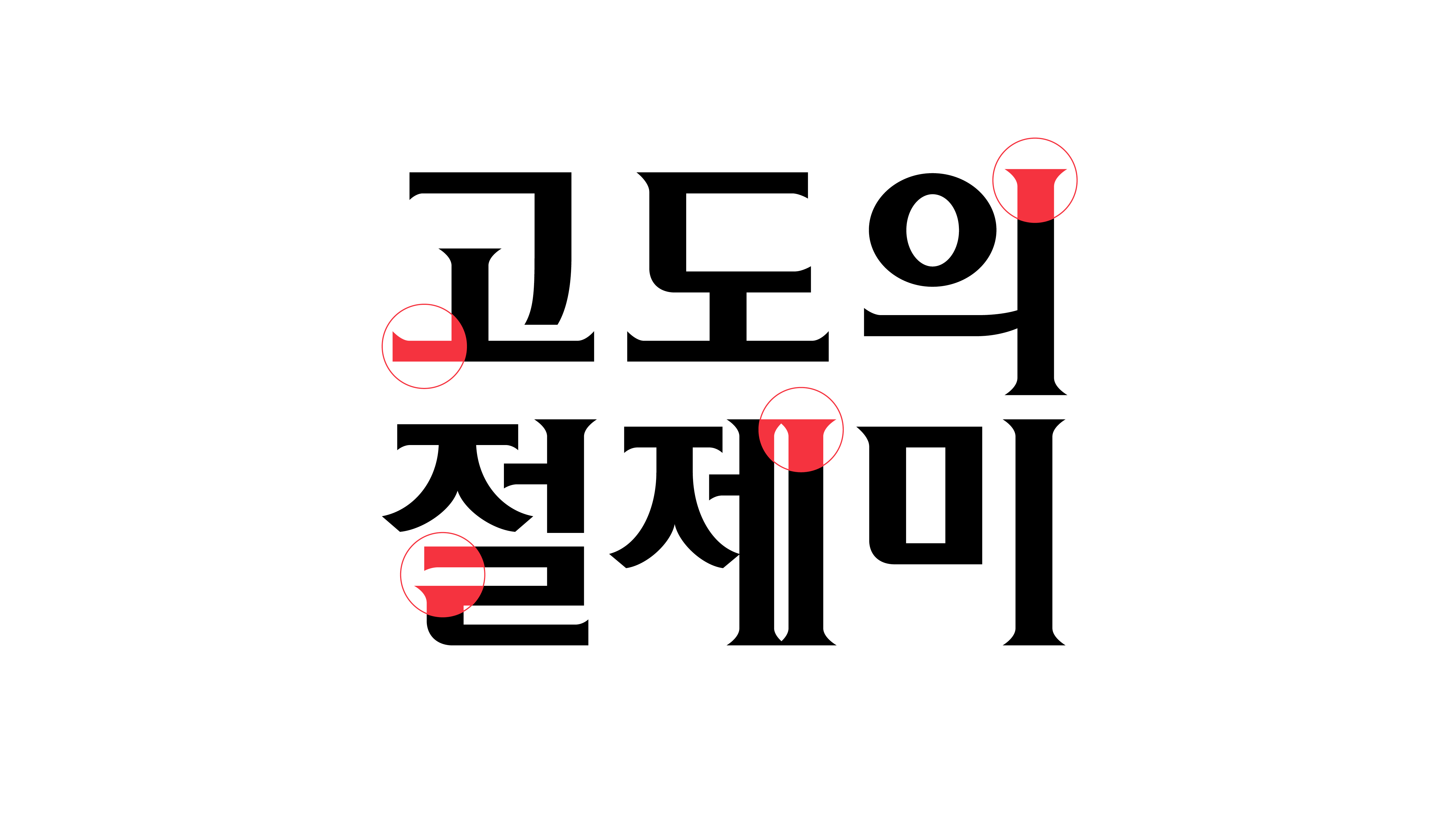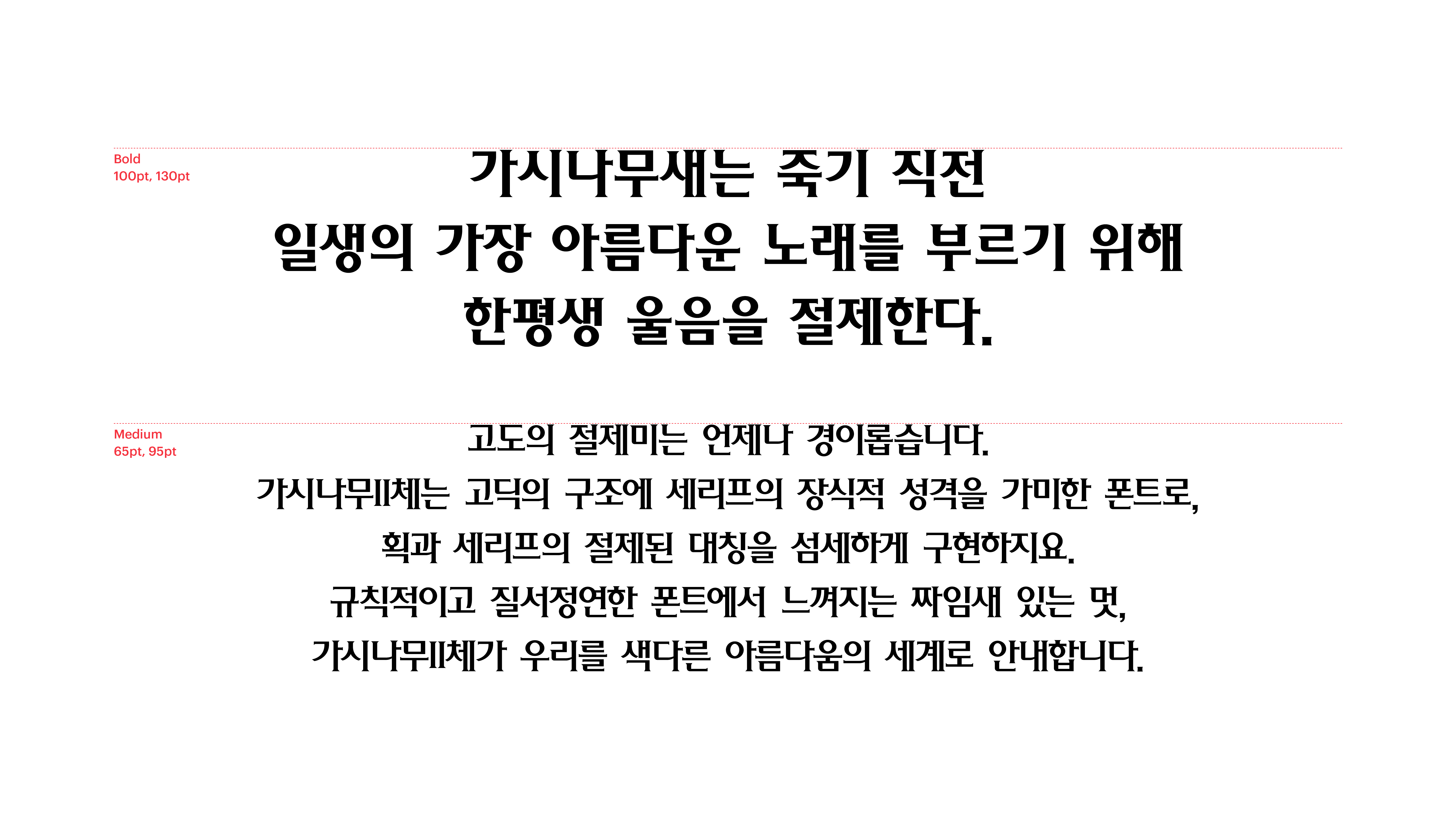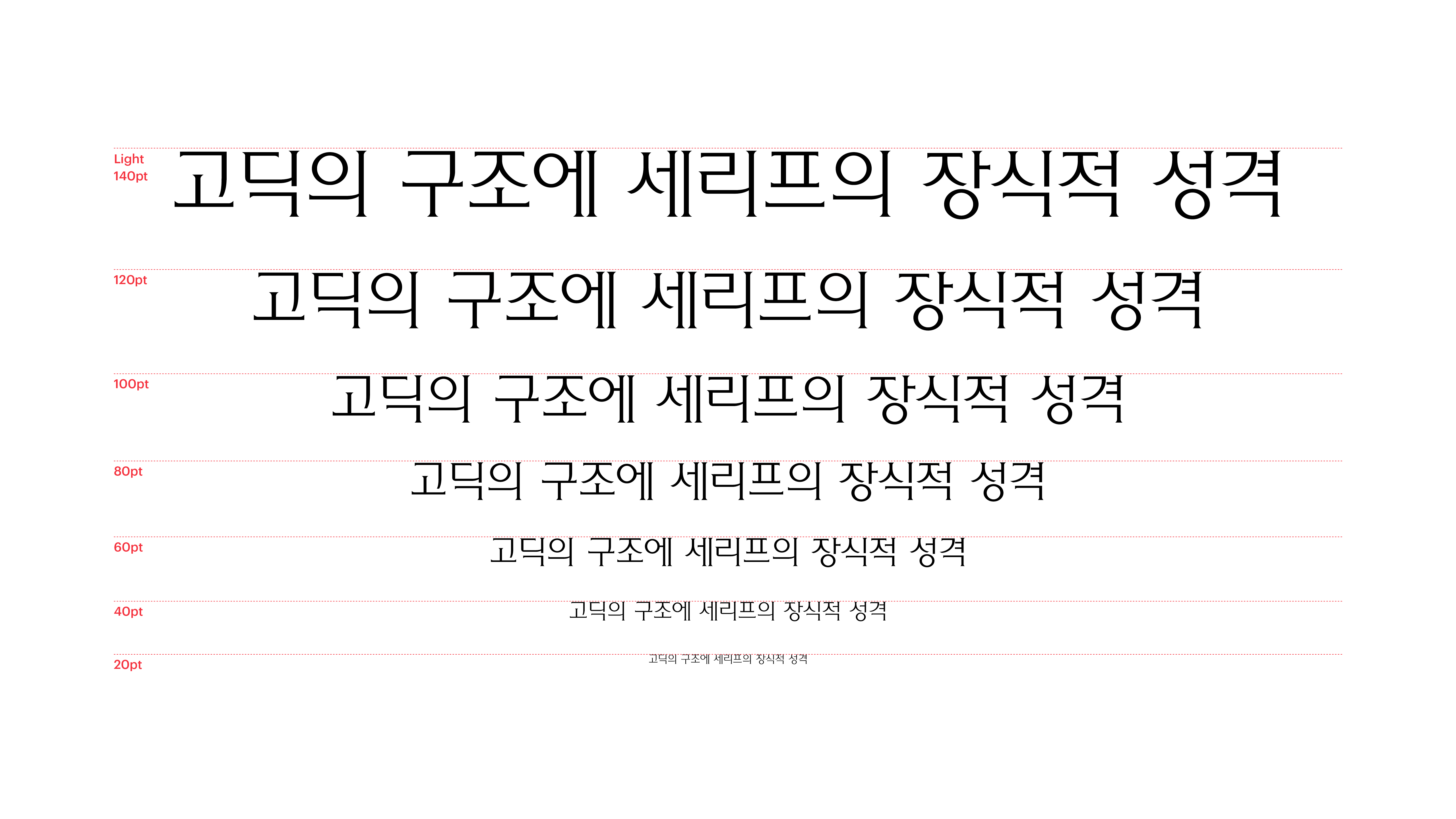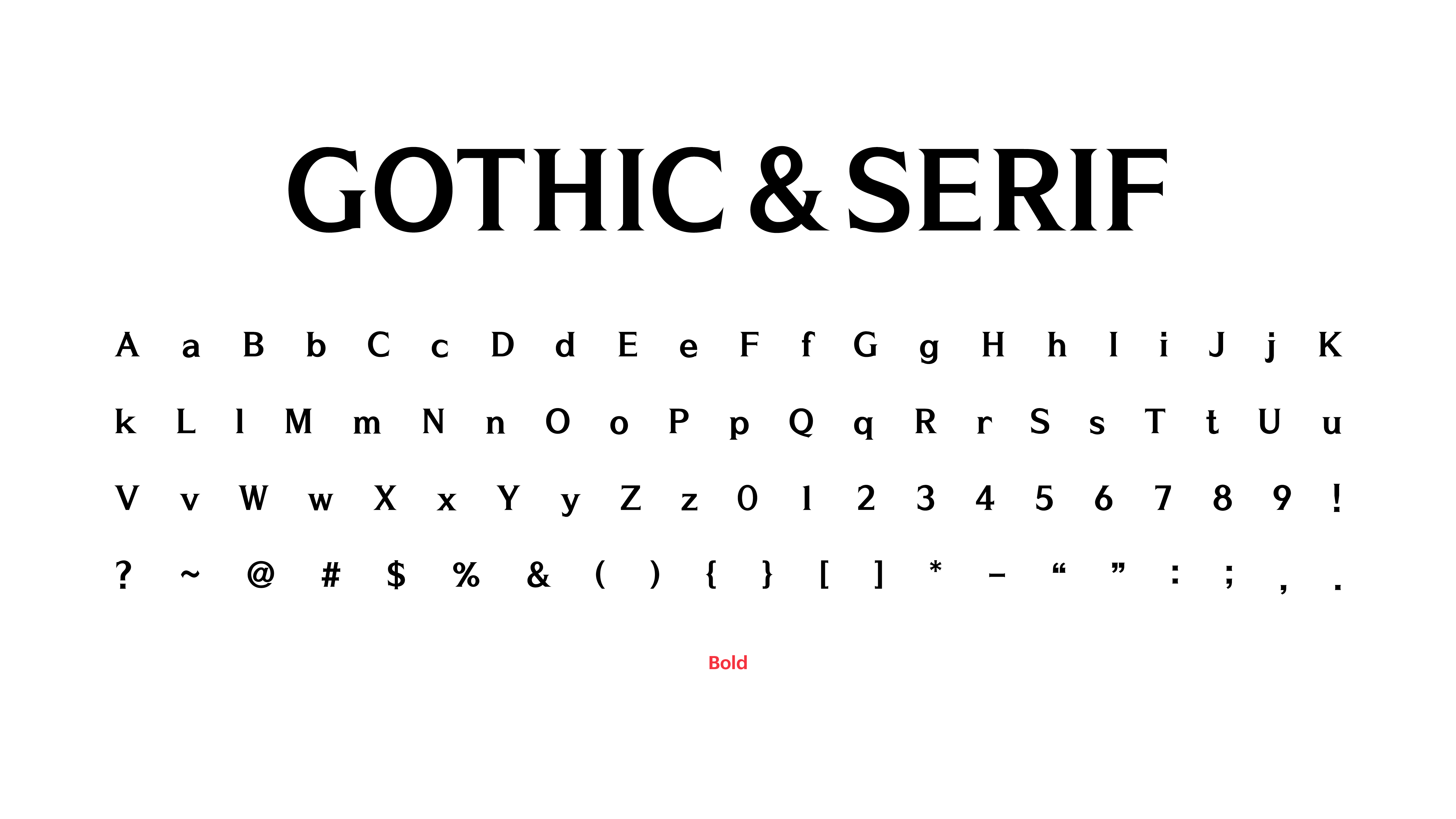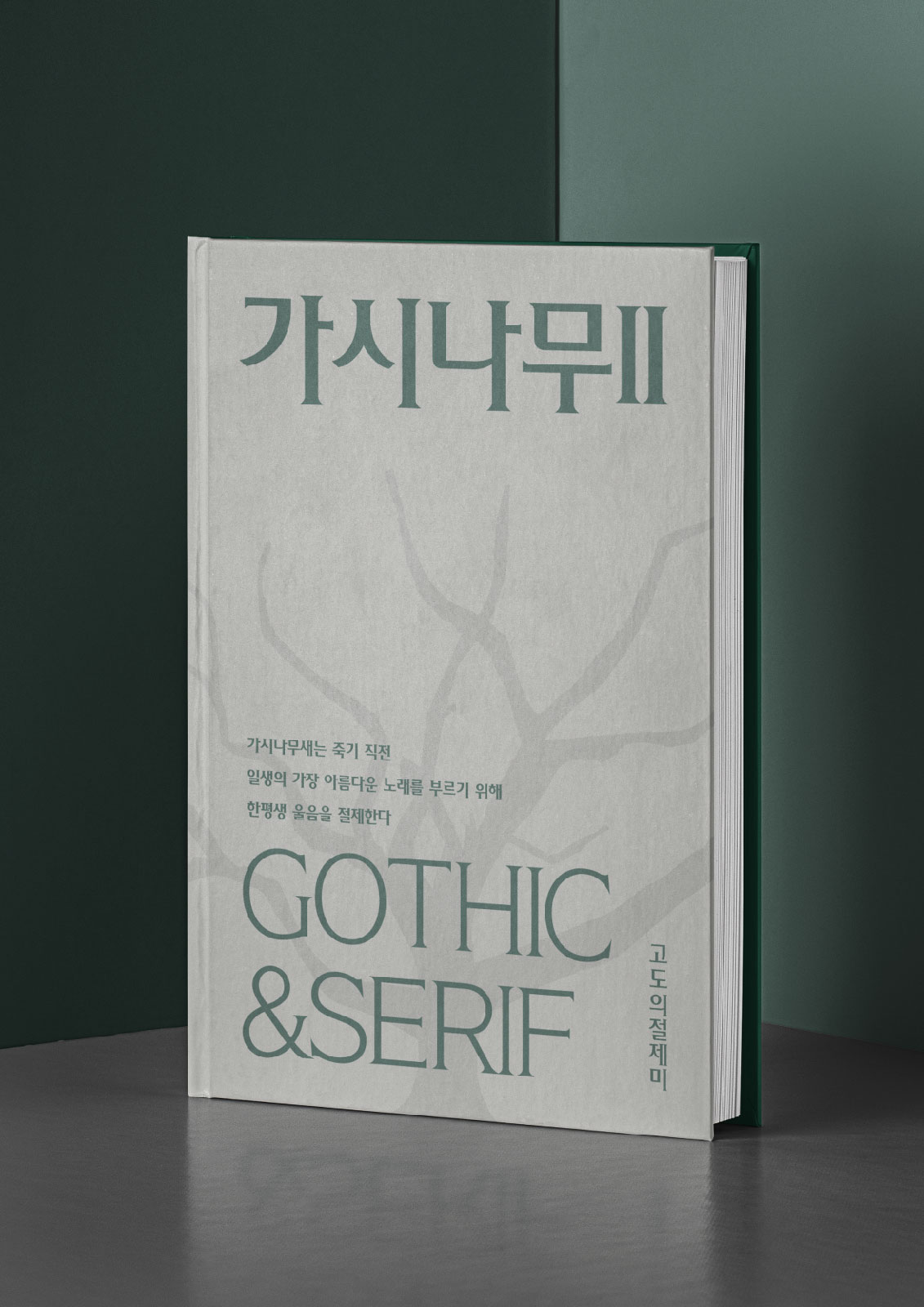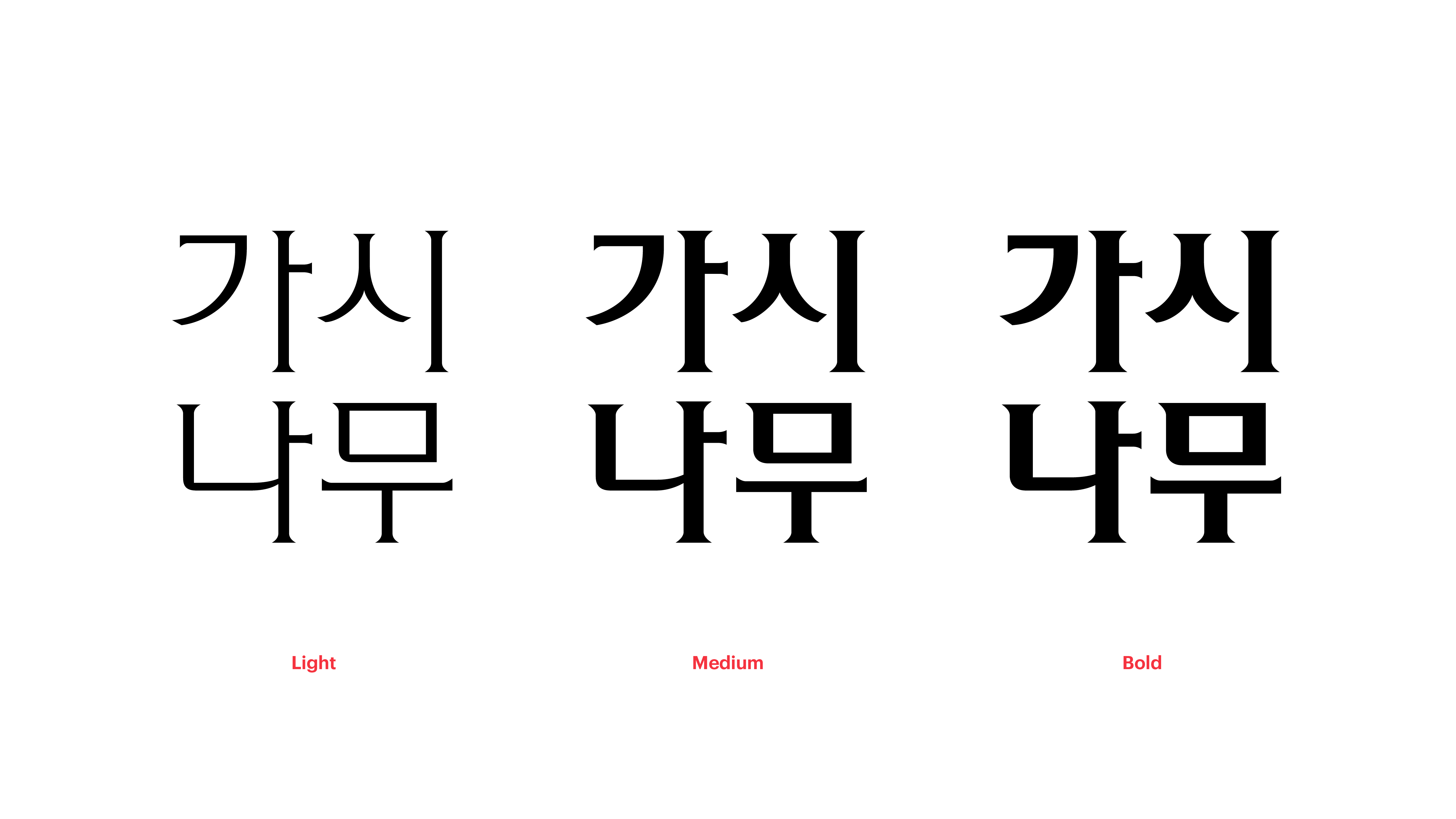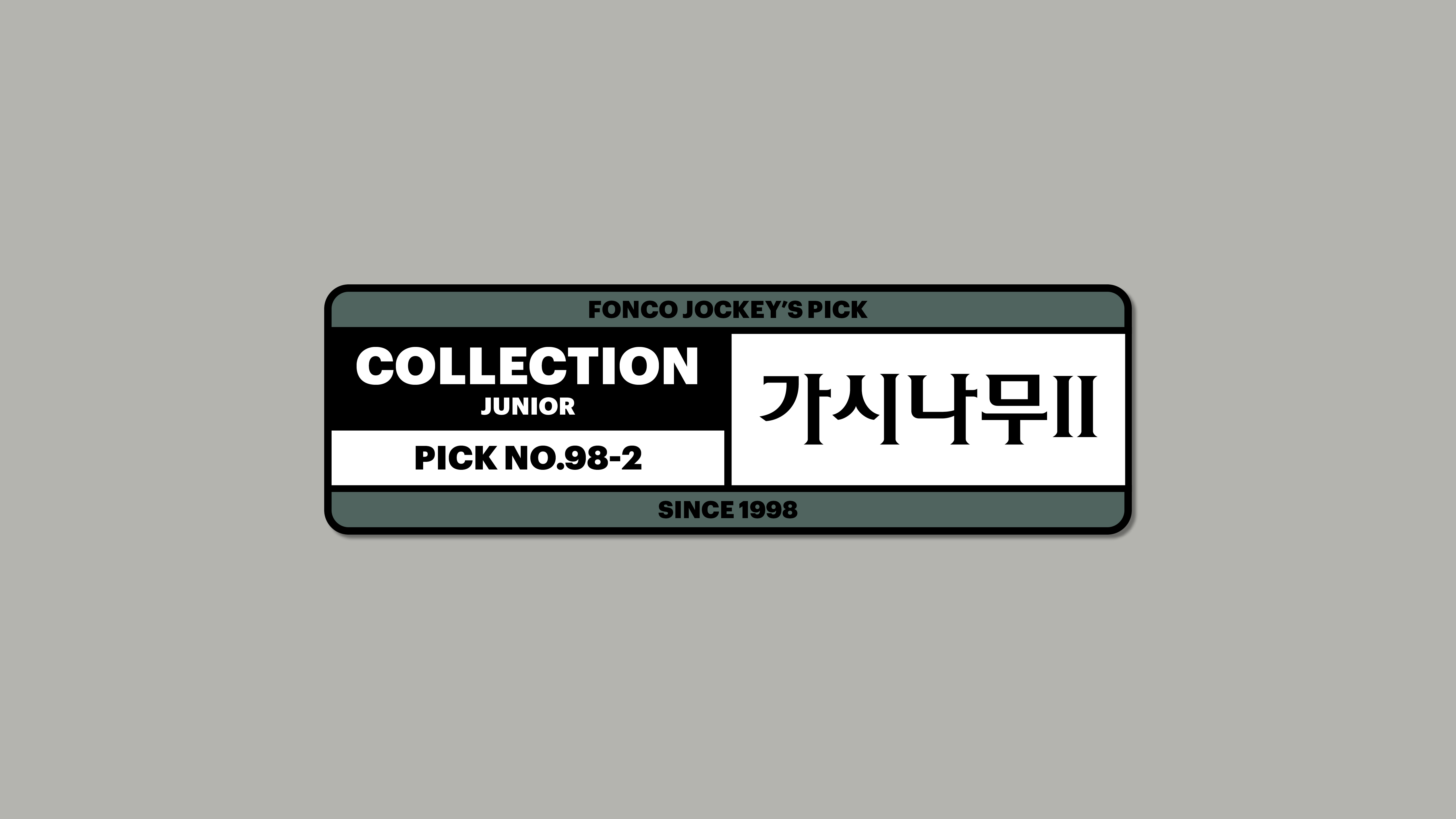
가시나무II
Yoon 가시나무II
고도의 절제미는 언제나 경이롭습니다. 가시나무II체는 고딕의 구조에 세리프의 장식적 성격을 가미한 폰트로, 획과 세리프의 절제된 대칭을 섬세하게 구현하지요. 규칙적이고 질서정연한 폰트에서 느껴지는 짜임새 있는 멋, 가시나무II체가 우리를 색다른 아름다움의 세계로 안내합니다.